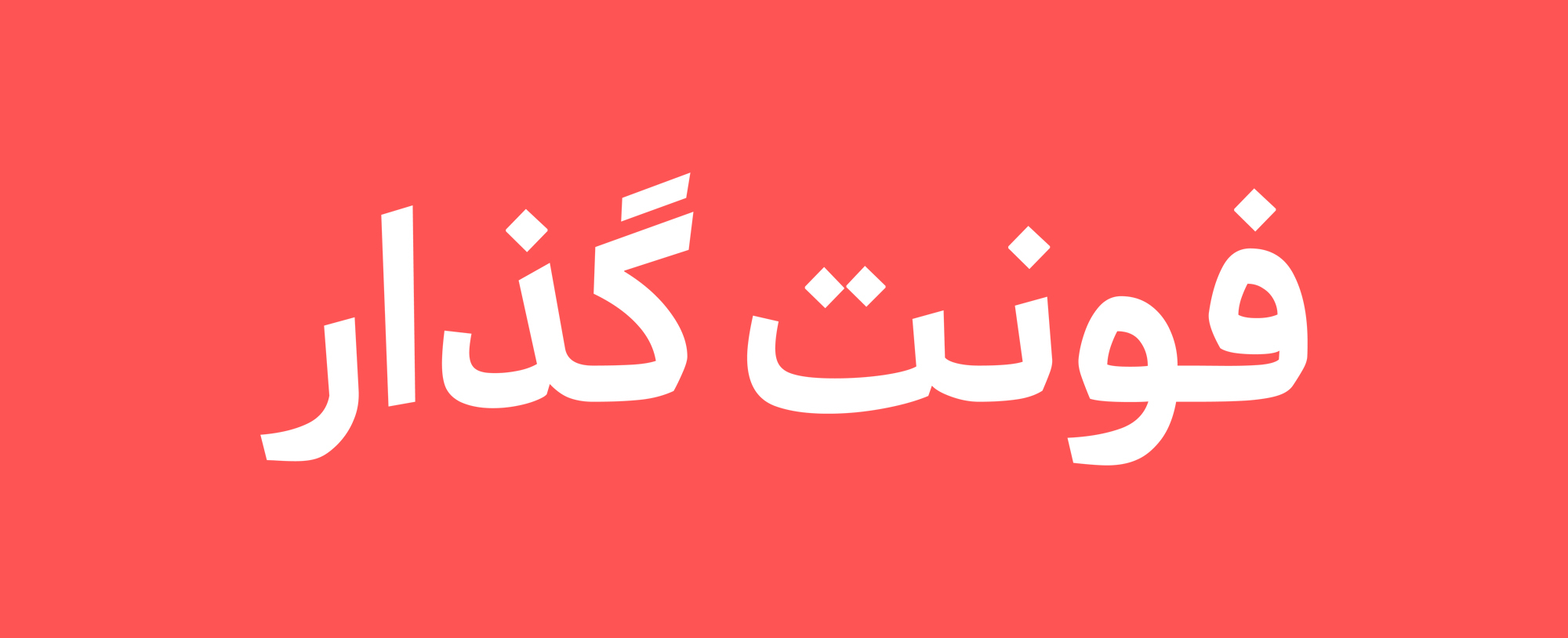
فونت گذار
فونت گذار  با وجود حفظ سبک رسم الخط نسخ تا حد زیادی به فونت‌های سنس (ضخامت یکسان) شباهت دارد. همین باعث شده با وجود روحیه اصیل مدرن و امروزی باشدو
فونت گذار حاصل دوساله تلاش و حل چالش های بسیار بوده ، از جمله ی این چالش ها می‌توان به ایجاد وجه تمایز با سایر فونت‌ها و همچنین حفظ زیبایی ، علیرغم کاربردی بودن آن اشاره کرد .
فونت گذار انتخاب مناسبی برای متن کتاب و مطبوعات و همچنین طراحی وبسایت و نرم افزارهایی است که می‌خواهد حال و هوای اصیل و فرهنگی داشته باشند.
تمامی حروف و مفردات با  حفظ  استقلال خود دارای فرم های یکپارچه  هستند که رفتارهای نمایشی در وزن های بالا بیشتر به چشم می خورد .